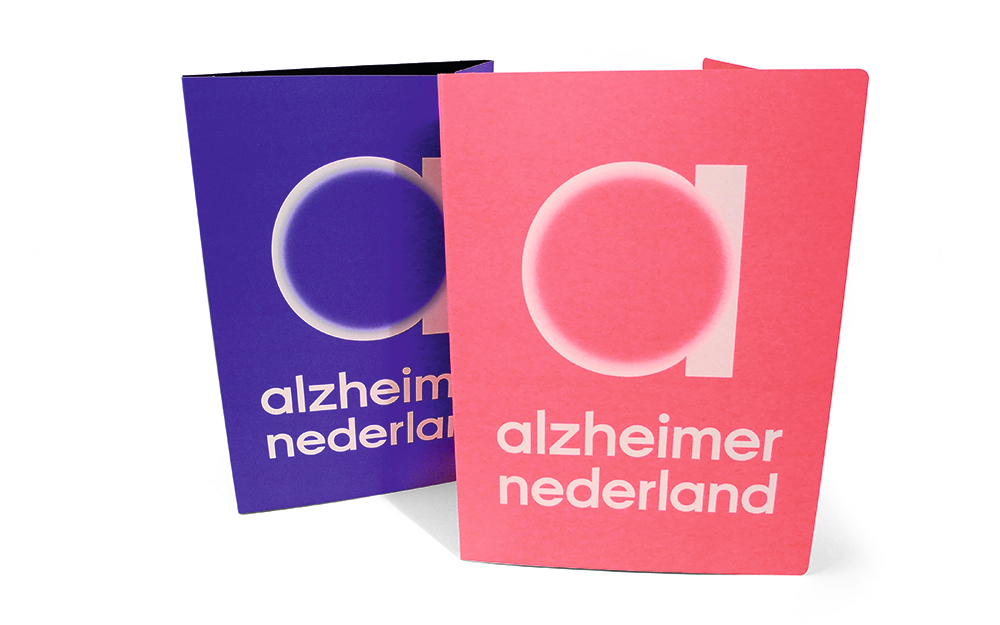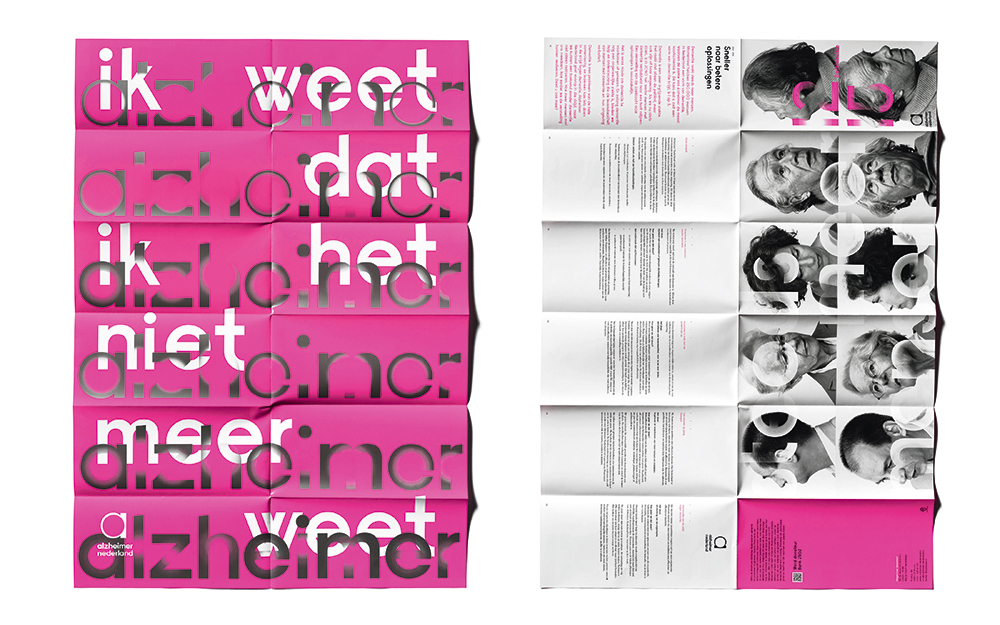
타입의 미래 : THE FUTURE OF TYPE
디자이너가 아닌 많은 사람들도 이제는 명함이나 웹페이지, 결혼초대장에 쓰이는 타입페이스를 옷이나 차에 견줄 만큼 중요한 의미를 부여한다. 타투부터 세계적인 브랜딩에 이르기까지 타입페이스 선택은 이제 그 어느 때보다 중요해졌다.
타입의 미래 : THE FUTURE OF TYPE
오늘날의 타입이 과연 단단한 토양과 규칙 위에서 실험이 허용되는 지속적인 분야로 자리 잡은 것인지 아드리안 쇼네시와 함께 탐구해 본다.
타이포그래피는 뜨거운 주제다. 많은 학생들의 학위 논문에 단골 주제로 등장하고 대중적인 토론회에서 자주 거론될 만큼 타이포그래피는 지적 탐구의 대상으로 자리 잡았다. 예전 같으면 거리를 오가는 평범한 사람들이 ‘바스커빌’이나 ‘헬베티카’를 알 필요가 전혀 없었다. 그러나 지금은 누구나 타이포그래피에 대한 선호와 견해를 표현할 수 있는 수준에 이르렀다. 디자이너가 아닌 많은 사람들도 이제는 명함이나 웹페이지, 결혼초대장에 쓰이는 타입페이스를 옷이나 차에 견줄 만큼 중요한 의미를 부여한다. 타투부터 세계적인 브랜딩에 이르기까지 타입페이스 선택은 이제 그 어느 때보다 중요해졌다.
이 같은 사실은 오늘날의 그래픽 디자이너와 타이포그래퍼에게 좋은 소식이다. 텍스트를 보완하는 단순한 그래픽의 역할을 뛰어넘어 타이포그래피로 창조적 표현을 할 자유가 과거보다 훨씬 많이 보장되고 있다. 이런 표현의 자유는 타입을 비틀고 겹쳐서 추상적인 형태를 만들어 내거나 아예 새로운 타입페이스를 창조하는 식으로 드러난다. 새로운 타입페이스의 창조는 오늘날 점점 더 보편적인 방식이 돼가고 있다. 디자이너와 타이포그래퍼는 기존의 타이포그래픽 전통을 근본부터 바꾸기 시작했으며 실험을 당연한 것으로 여기고 있다. 디자이너에게는 12개의 타입페이스만 있으면 된다는 이론은 이제 낡은 것으로 취급받기 시작했다.
물론 과감한 타입과 규범을 탈피하려는 타이포그래퍼들은 언제나 존재해 왔다. 모호이너지(Moholo-Nagy)의 초기 실험들과 그의 ‘타이포포토(typophoto)’ 이론, 1980년대 네빌 브로디(Neville Brody)가 <페이스>라는 잡지를 통해 보여준 표현력 넘치는 ‘타입 그림(painting with type)’, 그리고 상상을 초월하는 오늘날의 소프트웨어 기반 타입페이스 등 타이포그래피는 기존의 타이포그래픽 형태에 만족하지 못하는 디자이너들에 의해 꾸준히 응용되고 변화되어 왔다.
실험적인 타이포그래피는 더 이상 전위적인 존재가 아니다. 디자이너 헤자니 다우 벨루(Rejane dal Bello)가 네덜란드의 스튜디오 둠바에서 일하던 시절 만들었던 알츠하이머 재단의 타이포그래피가 이를 증명하는 대표적인 예다. 과감하게 비튼 타입의 강렬한 표현이 브랜딩에 반영되면서 이 타이포그래피 작품은 거의 전 세계적 차원에서 꾸준한 소통 능력을 발휘하고 있다.
현대 타이포그래피에서 이러한 자유가 의미하는 바는 무엇일까? 규칙에 얽매이지 않고 원하는 대로 할 수 있다는 뜻일까, 아니면 더 이상 나아갈 데가 없는 지나친 방종을 누리고 있는 것일까?
헤자니 다우 벨루(REJANE DAL BELLO), REJANEDALBELLO.COM
헤자니 다우 벨루는 런던에서 활동하는 그래픽 디자이너이자 일러스트레이터다. 리우데자네이루가 고향인 그녀는 스튜디오 둠바, 울프 올린스를 포함한 여러 브랜딩 디자인 회사들에서 일했다. 지금은 ‘스튜디오 헤자니 다우 벨루’를 운영하면서 세계적인 클라이언트들을 상대로 시각적 브랜딩 및 시각적 아이덴티티 작업을 하고 있다.
개인적으로 타이포그래피를 대하는 철학이 있다면 무엇입니까?
굳이 말하자면, 신경 쓰지 않는 게 제 철학입니다. 그냥 타입을 이미지처럼 대할 뿐입니다. 이는 어떤 창조적 입장에서가 아니라, 제가 6살 때부터 읽고 쓰는 데 어려움을 느껴 왔던 경험에서 비롯된 철학이에요. 당시 난독증은 병으로 인식되지 않았습니다. 그래서 치료를 받지는 못하고 수업이 끝난 뒤 학교에 남아 따로 교육을 받아야 했죠. 저는 모든 글자들을 시각적으로 인식했습니다. 단어의 의미는 그저 어림짐작으로 이해했고요. 이런 과거는 제가 어떻게 디자이너가 되었는지를 짐작하게 해주죠. 저는 모든 것을 하나의 형태 혹은 일러스트레이션으로 받아들였습니다. 그래서인지 길이가 긴 편집 디자인 프로젝트에는 마음이 가질 않죠. 복잡한 의미를 개념적으로 축약해서 단순한 상징적 이미지로 변환시키는 것에 흥미를 느낍니다. 이런 성향은 대체적으로 디자인과 관련된 직업을 유지하는 데 결코 불리하지 않습니다.
타이포그래픽 전통, 즉 규칙과 관습 등이 당신에게 어떤 영향을 미칩니까?
규칙과 관습을 깨려면 우선 그것들이 무엇인지를 정확히 알아야 합니다. 저는 늘 시각화에 필요한 핵심 요소가 무엇인지를 가장 중요하게 생각합니다. 따라서 규칙과 관습이 거기에 도움이 될 땐 주저 없이 따릅니다. 그러나 보통은 우리가 ‘황금률’이라고 부르는 것에 저항함으로써 프로젝트의 한계를 뛰어넘으려고 노력합니다. 단순히 반항의 의미로서가 아니라 새로운 전통을 창조하는 것이 우리의 역할이라고 믿기 때문이죠. 또한 그렇게 함으로써만이 새로운 길을 열고 개척할 수 있으니까요.
많은 디자이너들이 오늘날 새로운 타입페이스 제작에 몰두하는 모습을 보이는데 그 이유는 무엇이라고 생각합니까?
세상에는 이미 아름답고 기능적이고 실험적인 타입들을 너무나 많기 때문에 디자이너들이 더 이상 새로운 타입을 필요로 하지 않을 것이라고 생각하기 쉽습니다. 그러나 어떤 새로운 것이 등장할 수 있을지는 아무도 모르죠. 새로운 것이 필요 없다는 생각은 사람들에게 더 이상 호기심을 갖지 말라는 것과 다름없습니다. 그러나 호기심이야말로 창조적인 사람들에게는 없어선 안 될 힘입니다. 단지 유행을 따르려는 의도에서 새로운 것을 추구해선 안 되겠죠. 사람들은 종종 유행에 충실한 것이 성공의 지름길이라고 착각합니다. 이는 완전히 잘못된 생각이죠. 그러나 새로운 타입 제작이 당신에게 중요하다면 해야 합니다. 세상에 존재하는 타입의 숫자가 당신을 막을 수는 없습니다.
최근 타이포그래피와 관련해서 당신의 관심을 끄는 건 무엇인가요?
두 가지가 제게 감동을 줬습니다. 하나는, 1930년대 바실리 칸딘스키(Vasily Kandinsky)의 색채이론을 교육하는 과정에서 하인리히 지그프리트 보만(Heinrich Siegfried Bormann, bit.ly/kandinsky-theory)이 음악을 시각적으로 분석한 작업입니다. 엄밀히 말하면 폰트는 아닌데, 충분히 그렇게 읽어낼 수 있는 작품이죠. 다른 하나는 뤼디 휘드이(Rudy Guedj, rudyguedj.com)가 만든 ‘클리프(Kliff)’ 폰트입니다. 정말 기묘하고 독특하죠!
오어 타입(OR TYPE), ORTYPE.IS
오어 타입은 2013년 그뷔드뮌뒤르 울바르손(Guðmundur Ulfarsson)과 마스 프로인트 브륀세(Mads Freund Brunse)가 결성한 GUNMAD의 타입페이스를 발행하기 위해 설립된 타입 파운드리다. 맞춤형 타입 프로젝트와 라이선스를 다루면서 결과적으로 새로운 알파벳 목록의 증가에 일익을 담당하고 있다.
당신들의 웹사이트를 보면 “우리는 타이포그래픽 전통과 관습에 도전하는 타입페이스를 추구합니다.”라고 적혀 있죠. 이에 대해 자세히 설명해 줄 수 있나요?
타입페이스 디자인은 좋든 나쁘든 지켜야 할 규칙이 많은 분야입니다. 우리는 타입페이스가 기존의 도구와 수단이 지닌 한계 때문에 결점을 가질 수밖에 없었다는 점에 주목합니다. 우리에게 가능한 수단들에 의해서만 글자들이 만들어질 수 있었다는 의미죠. 캘리그래피가 그 대표적인 수단입니다. 그러나 기술을 연마함으로써 어느 정도는 한계를 극복할 수 있죠. 우리는 현재 디지털 툴로 이 기술을 얼마나 신장시킬 수 있는지를 흥미롭게 살펴보고 있습니다. 오늘날 우리는 수백 년 전의 기준을 적용해서 결코 수백 년 전의 모습처럼 보이지 않는 완벽한 타입페이스를 만들 수 있습니다. 이런 모순된 현상이야말로 우리가 추구하고 구상하는 것입니다. 즉, 수백 전의 도구들을 가지고 현대적인 형태를 창조하는 거죠.
타입페이스를 디자인할 때 어디에서 아이디어를 얻습니까?
우리는 지금까지 보지 못했던, 상상을 뛰어넘는 참신한 타입페이스를 만들고 싶습니다. 타입의 세세한 부분에서부터 텍스트가 흘러가는 방식에 이르기까지 어떤 지점에서든 참신함은 추구될 수 있죠. 우리는 오로지 직관해 의지해 아이디어를 개발해 나갑니다. 친구들의 의견에도 귀를 기울이고요.
오늘날의 타이포그래피에 커다란 흐름이 있다면 무엇이라고 생각합니까?
타이포그래피 분야 전반에 걸쳐 많은 흐름들이 존재합니다. 오래된 프랑스 세리프나 깔끔한 리바이벌 버전의 독일 프락투어를 완전무결하게 다듬기, 스위스 산세리프의 현대적 정비, 특정 글자를 대체하는 깔끔한 심볼들로 기하학적인 대문자 산세리프를 만드는 실험 등이 진행 중이죠. 어디서 출발하고 어디서 끝이 날지 우리는 알 수 없습니다. 타이포그래피는 그 자체로 하나의 트렌드가 되었죠. 이는 좋은 현상이라고 우리는 믿습니다! 타이포그래피의 수준은 한층 높아졌고 우리는 흥미로운 타입페이스들을 끊임없이 발견하고 있습니다. 이런 현상이 앞으로도 더욱 강화되면서 사람들이 글자들을 읽는 방식에 변화를 줄 수 있었으면 합니다.
최근 당신들이 감동을 받은 타입페이스가 있다면요?
한동안 우리는 제레미 쇼데렛(Jeremy Schorderet, bit.ly/Schorderet)의 ‘다셔(Dasher)’ 타입페이스에 환호했습니다. 요즘에는 얀 노바크(Jan Novak, bit.ly/jannovak)의 작품에 빠져 있습니다. 그는 정말 특이한 글자 형태들을 창조하죠. 참 마음에 듭니다.